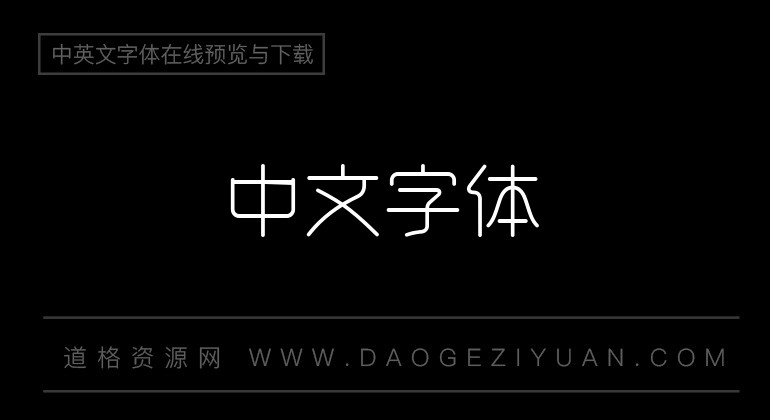
字心坊小令体细体
心坊小令体细体是一款中文字体,由字体心坊设计团队设计开发,具有简洁、清新的外观,字体细腻,曲线优美,拥有极佳的可读性,适合用于文字编辑、文字排版等方面。字体心坊小令体细体拥有多种字重,可以满足多种设计需求,是一款非常优秀的中文字体。
字心坊小令体细体是一款非常不错的手写艺术字体,具有很好的视觉感,适合于文化类的宣传设计、商业类品牌的广告和产品包装设计以及个性化文字排版等较多场景。